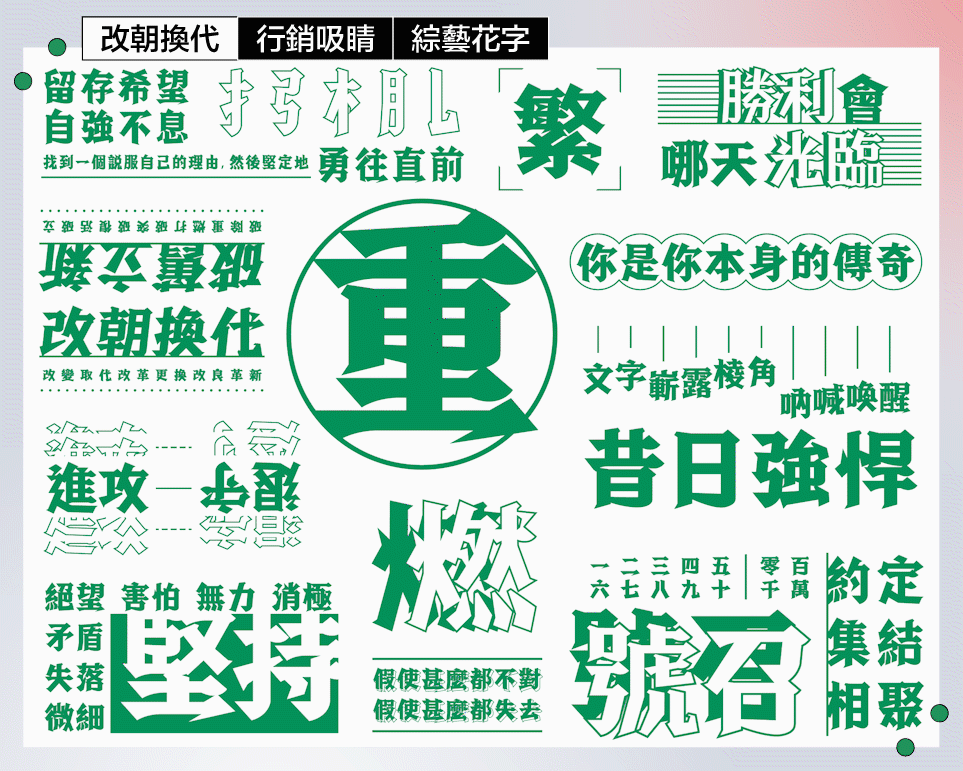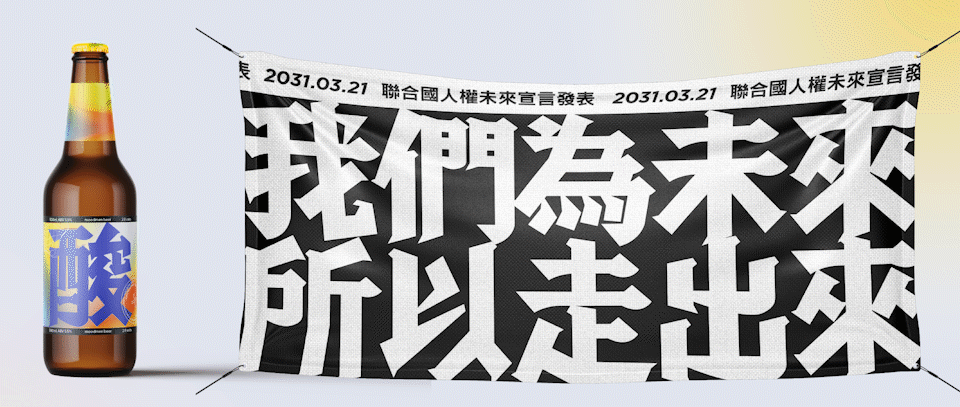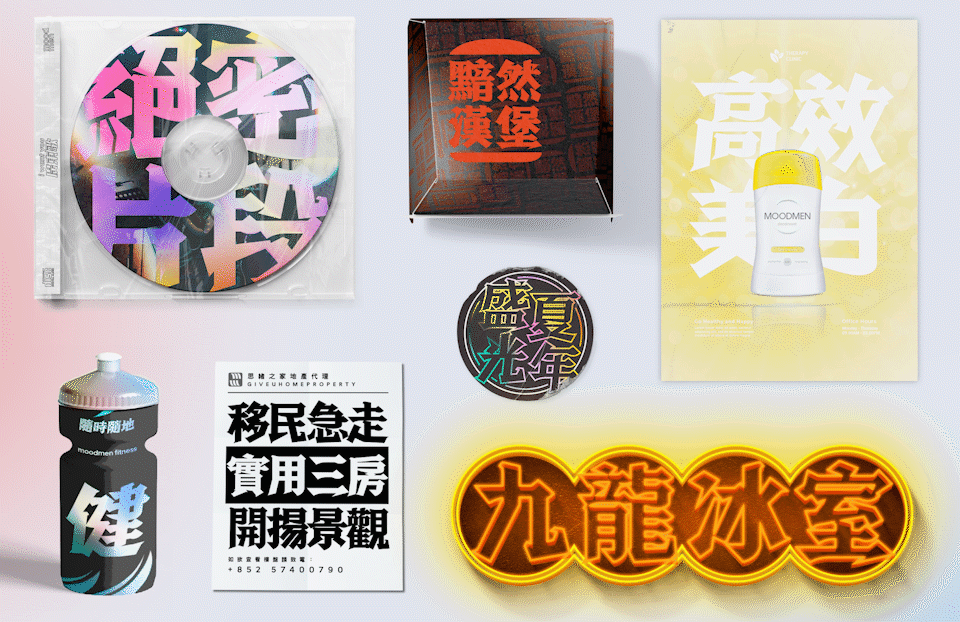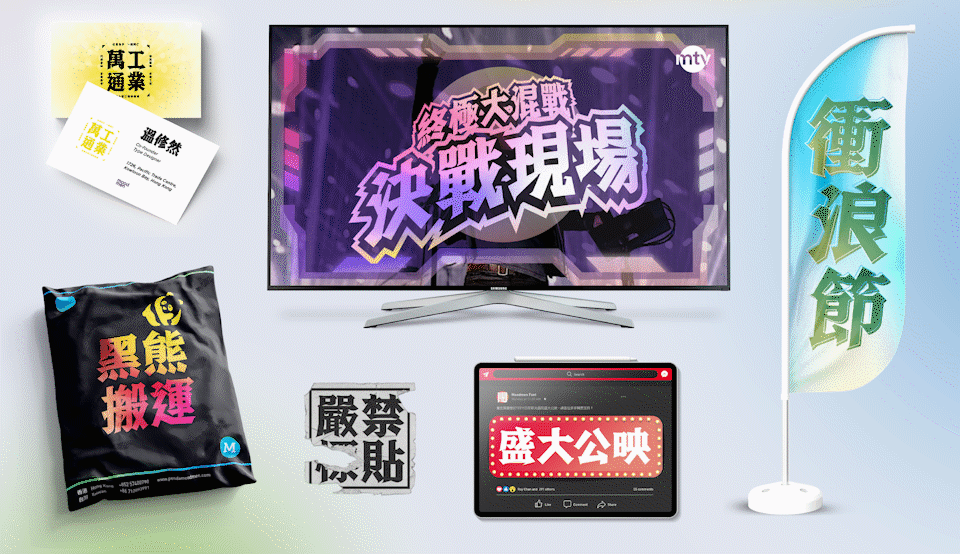
思緒重生體—新舊交融、棱角佈滿個性,旨在令文字涅盤重生。
有腳字的黑體設計,讓你的標題吸晴,顧客才有繼續閲續的興趣!
過往不夠號召力的商品、服務、群眾,換上思緒重生體,
讓一切重生再來。
思緒重生體|Reborn Font
5300 字繁體|正體/斜體|香港字型計劃
文字,是身份;字型,是靈魂。
香港這十年,變化快得令人追不上。街道、招牌、字形、語氣、口音、文化……一點點變淡、變少、甚至消失。
字體,是城市裏最安靜的見證。而思緒重生體,就係我對時代回應的方式。
|創作初心:重生,不是懷舊,是重新站起來
一段香港人都記得的日子。我開始問:
「如果有一款字體,可以凝住一種氣質、一種語調、一種不願放低的力量,會係點?」
我不急著懷舊,亦不浪漫化悲情。重生不是返去以前,重生是學會在傷痕上重建、在灰燼裏再長根。於是,「思緒重生體」誕生。
它不為迎合潮流,不為安全感。它粗獷、有棱角、帶反骨、帶火光是一種「我還在」的聲音。不是為了喚醒世界,是喚醒字體這個界別的靈魂。
|筆劃語言:硬朗、乾脆、帶呼吸感的力量
這套字體的語言很直接 – 黑體的實力+宋體的骨血。
粗壯直筆=倔強與站立|斜向起筆=像刀、像筆尖、有攻擊性|收筆扇形=擦過空氣的力量感|轉折乾脆=不拖泥帶水,像一句「講嘢講重點啦」
有人看它覺得沉重;有人覺得好「硬淨」;亦有人説:「好似睇緊一個人重新企返起身」。這不是一套平靜字體,它係活生生、有血、有肉的字。
|正體 vs. 斜體:兩種聲音,一個靈魂
正體:站穩
沉著、穩定、像深呼吸後的堅定。|用於:報告、書籍、品牌主字、標語、文化類出版
斜體:前衝
速度、張力、如疾走、如打氣、如心跳。|用於:廣告標語、運動、展覽視覺、海報、動態字幕
正體 vs 斜體
一個是「我在這裡」,一個是「我繼續向前」。
|收字—5300 字繁體|港式字形語感
字集𥚃有:
港式常用字形
傳統筆畫結構
正體+斜體各 5300 字
支援印刷/品牌/社群/動態
「繁體,是文化厚度;港式字型,是一種語氣。」每一筆都帶住地方感、情緒、位置感。
|為誰而設?
文字創作者/設計師
品牌、藝文組織
出版、展覽、文化項目
社交平台自媒體、片主
想保存語言與記憶的人
Reborn 不是單純視覺效果,而是一種精神。
|使用感:不需要懂排版,也能用得漂亮
這款字體有一個特別特性:就算排得簡單,也會有存在感。因為它本身帶呼吸感、節奏、自身能量。只要你輸入文字,它就會講故事。
建議:
大字標題效果極佳
黑白反差突出氣勢
搭配簡潔無襯線內文更突出
Creative Direction Tips:
留白+大字=震撼
密排+字框=強烈政治海報感
|一句話總結
這套字體不是為了看起來漂亮,是為了提醒你:我們仍然在。